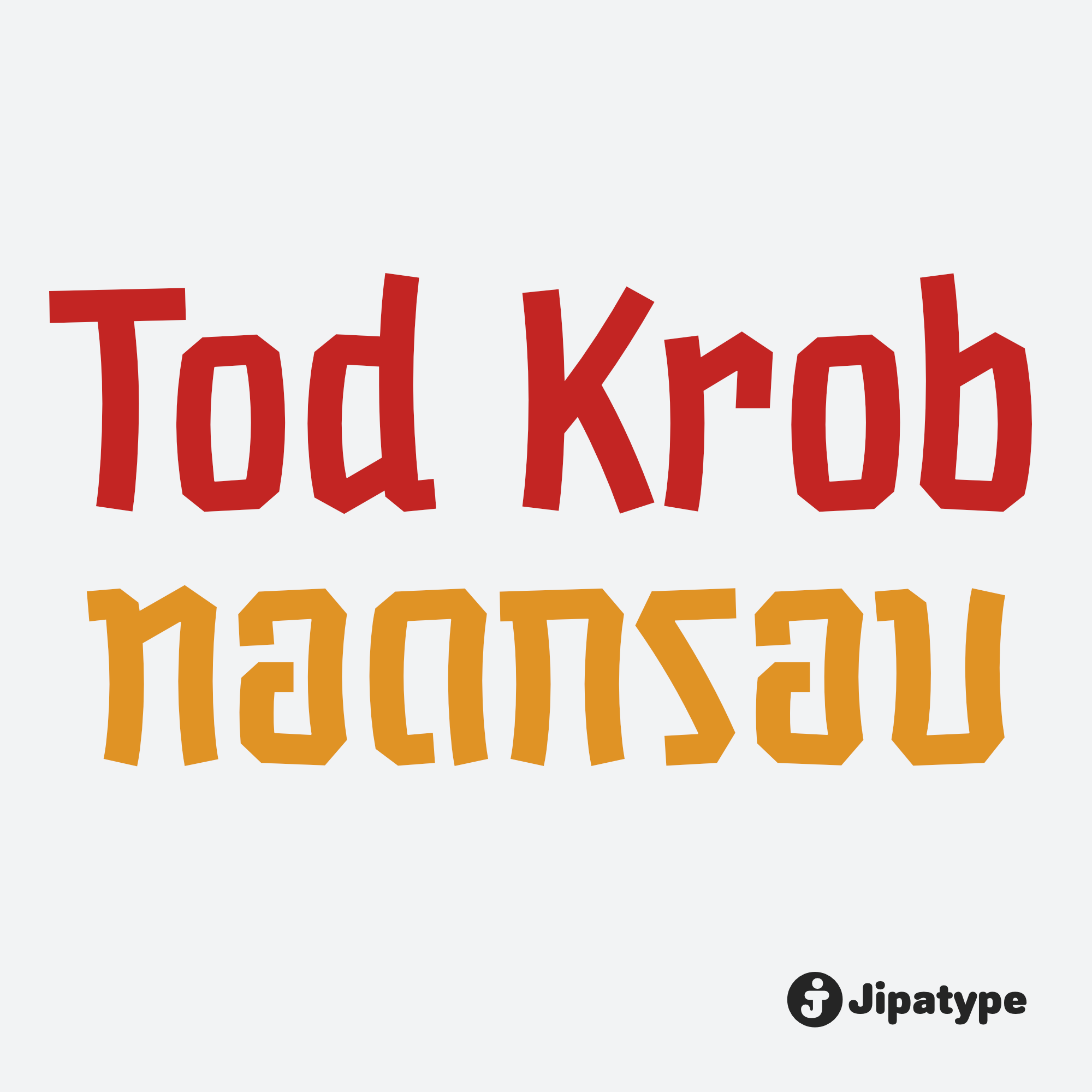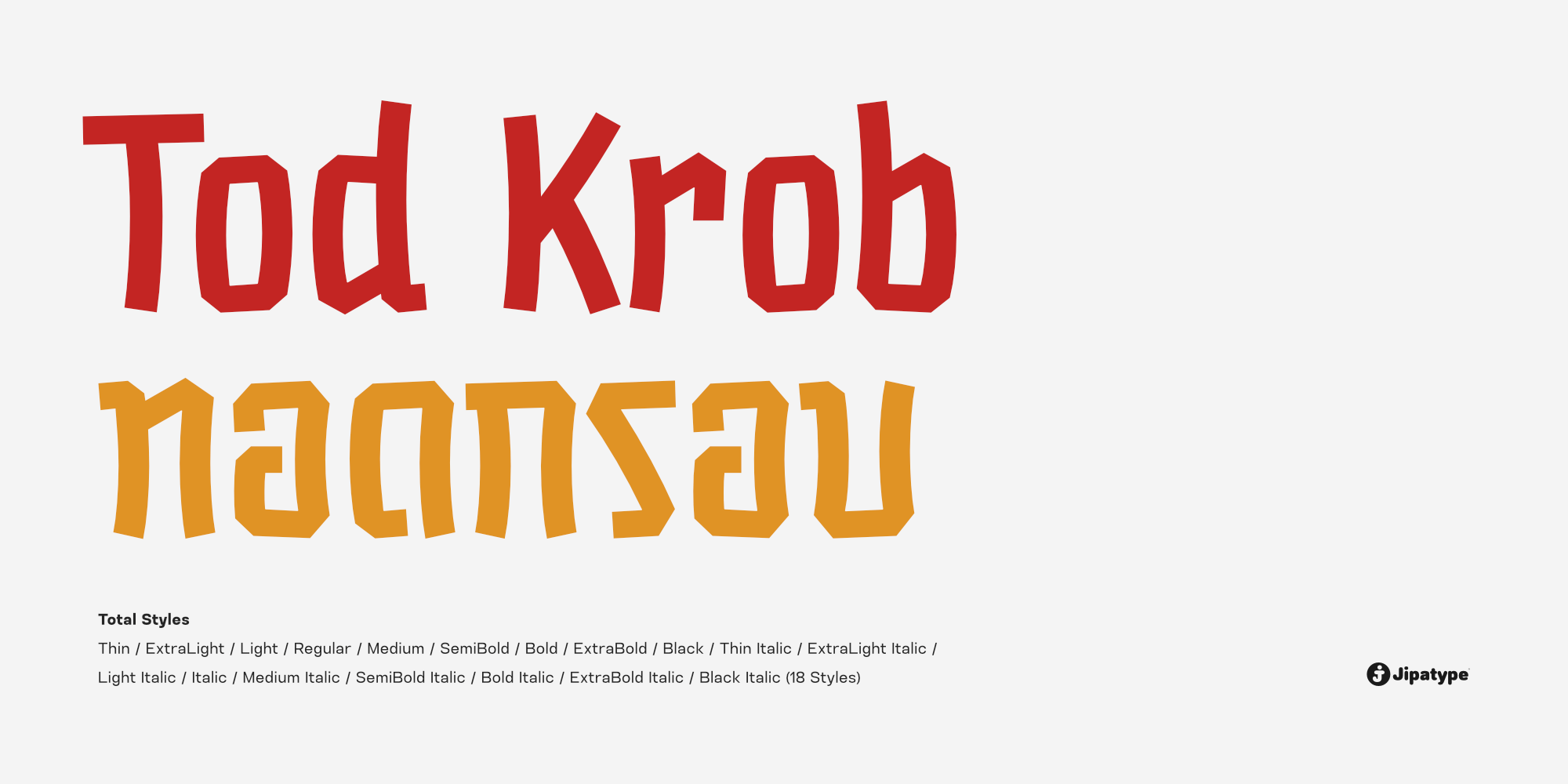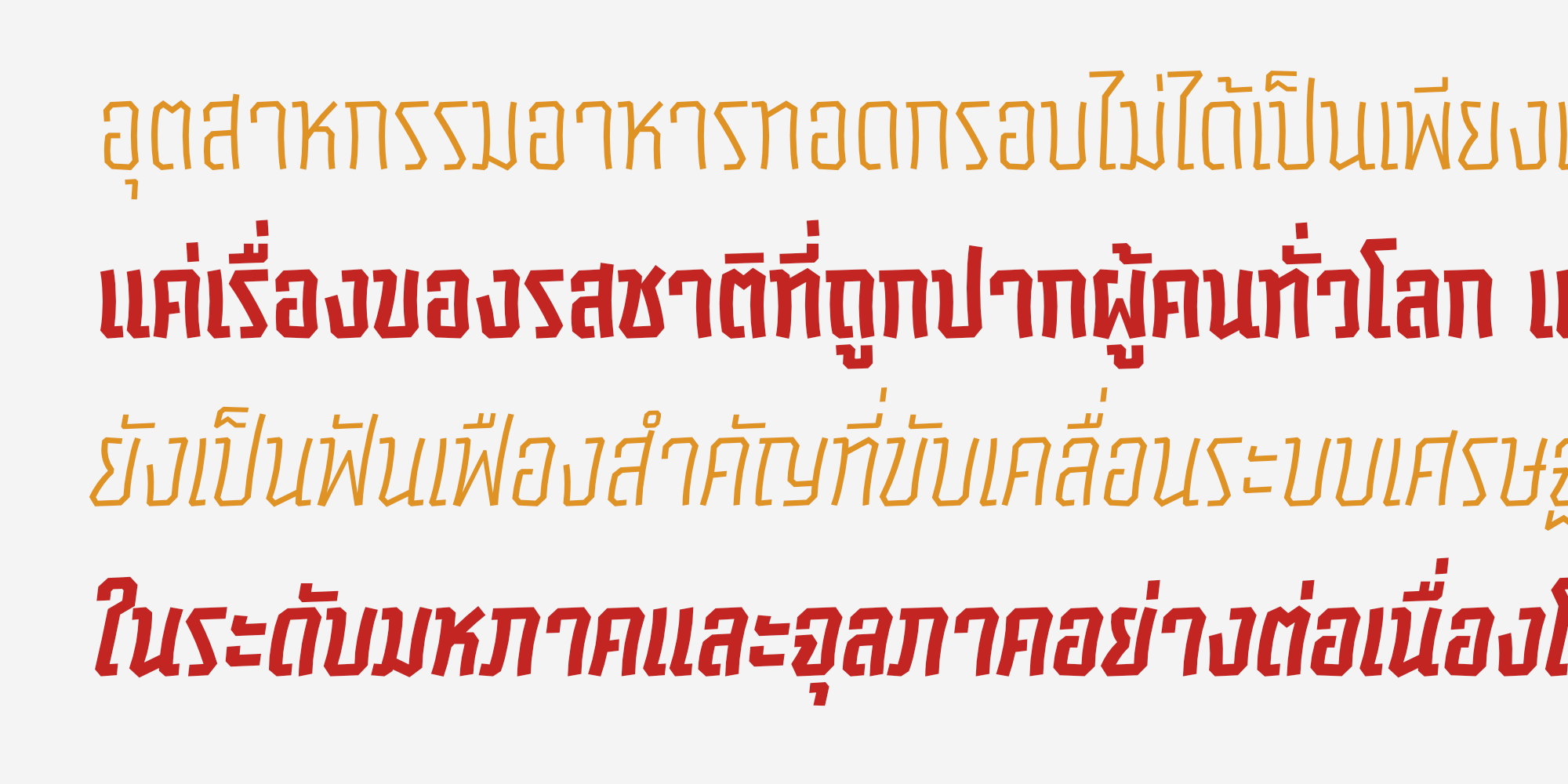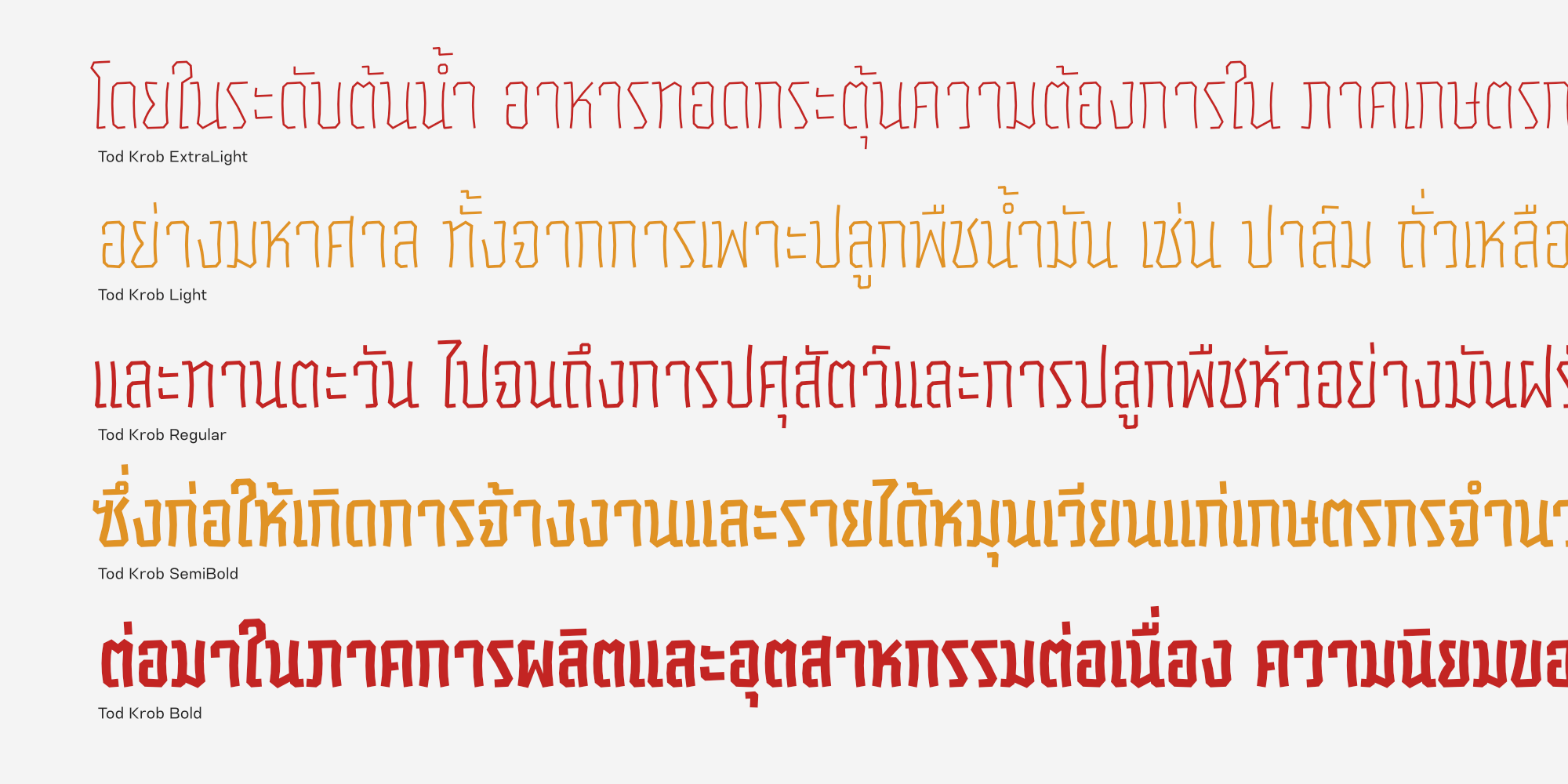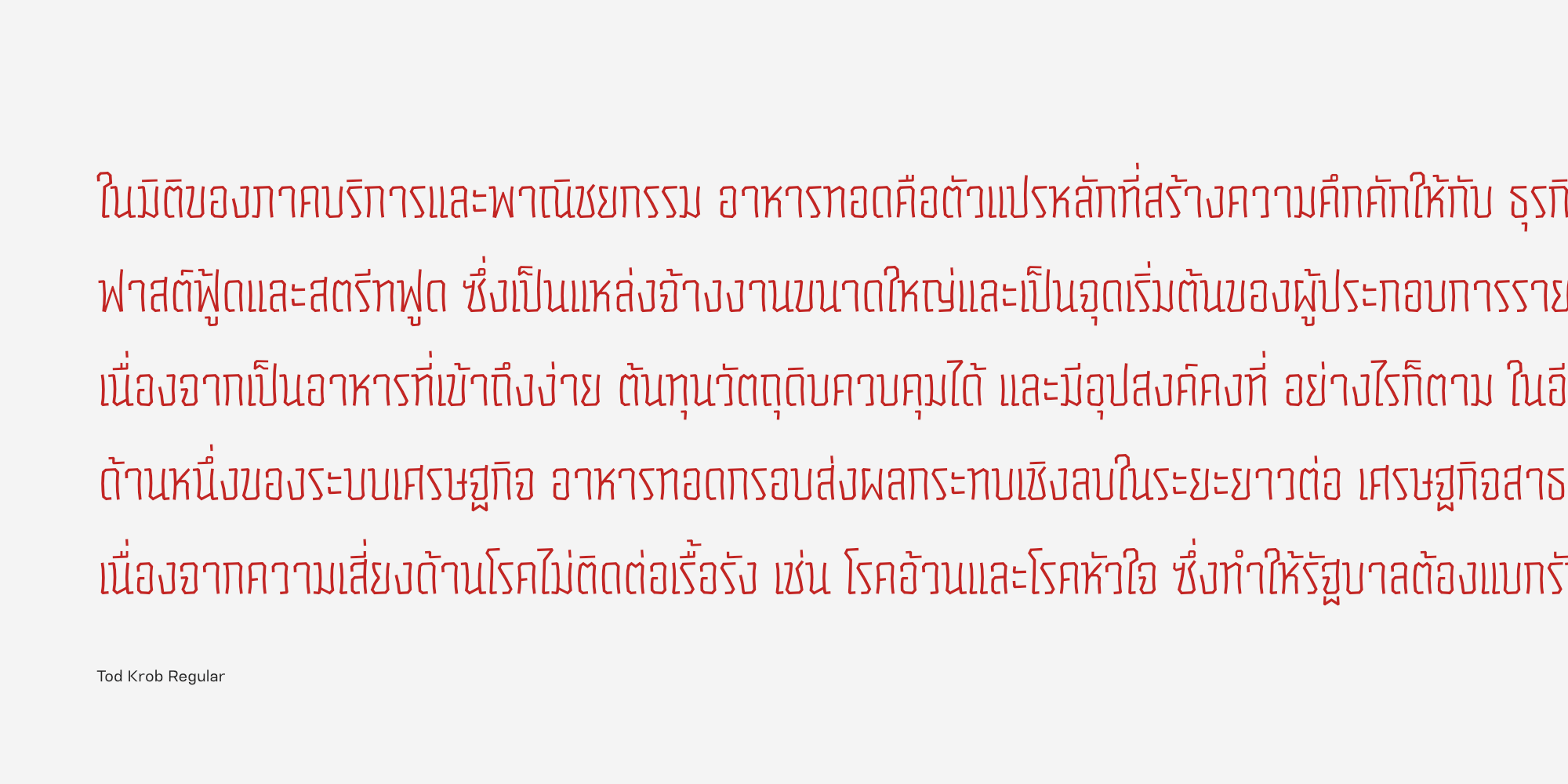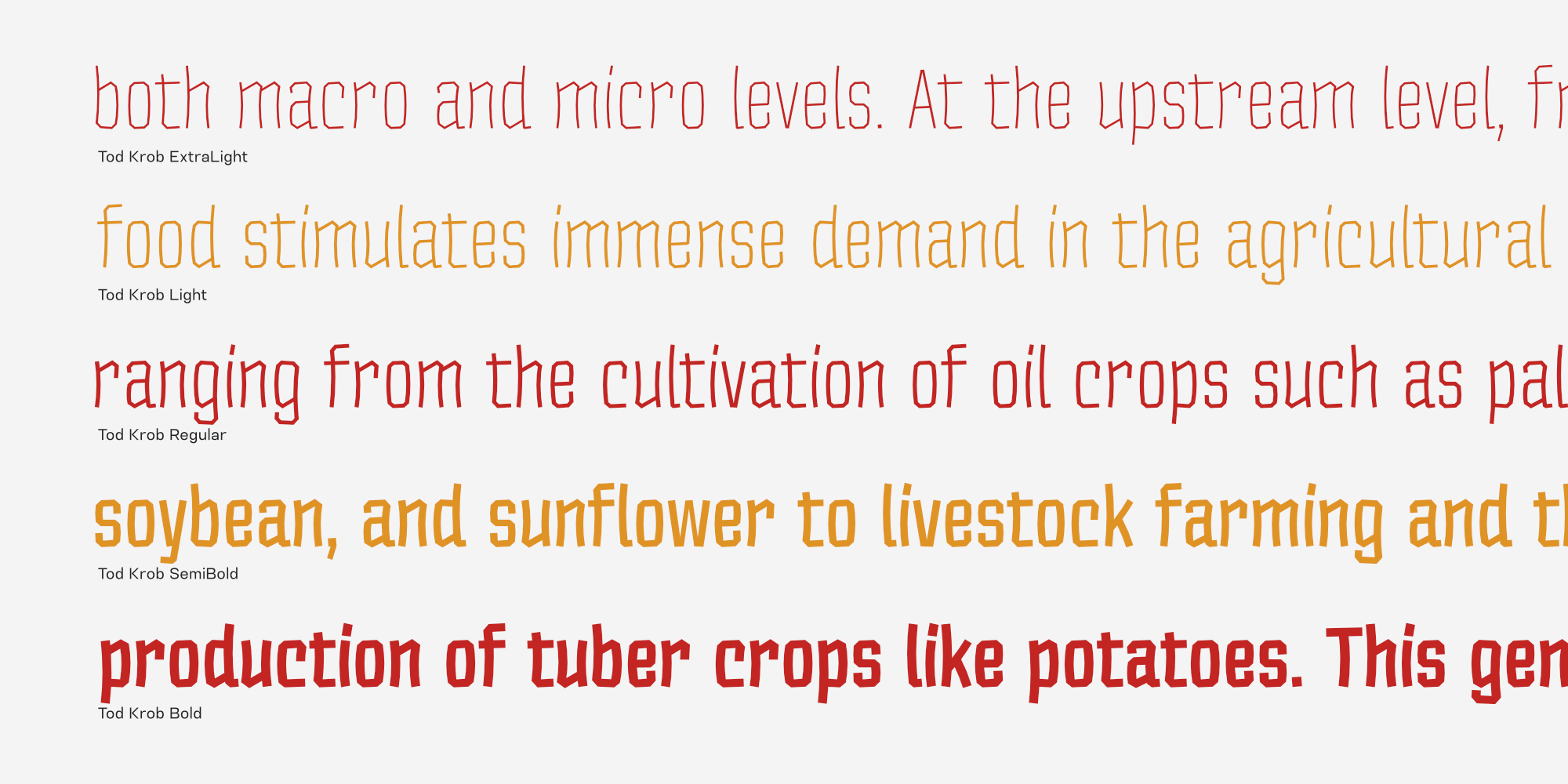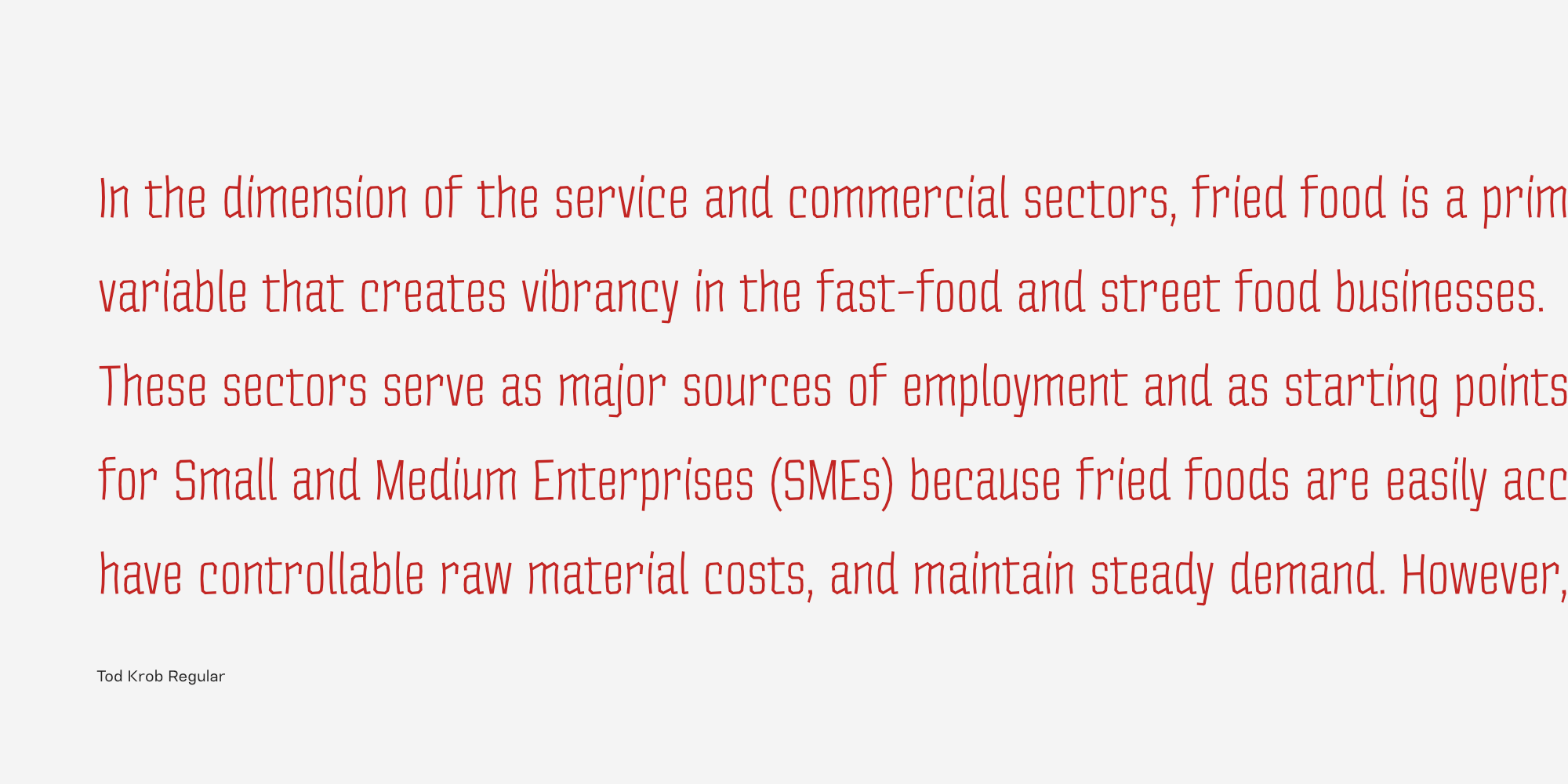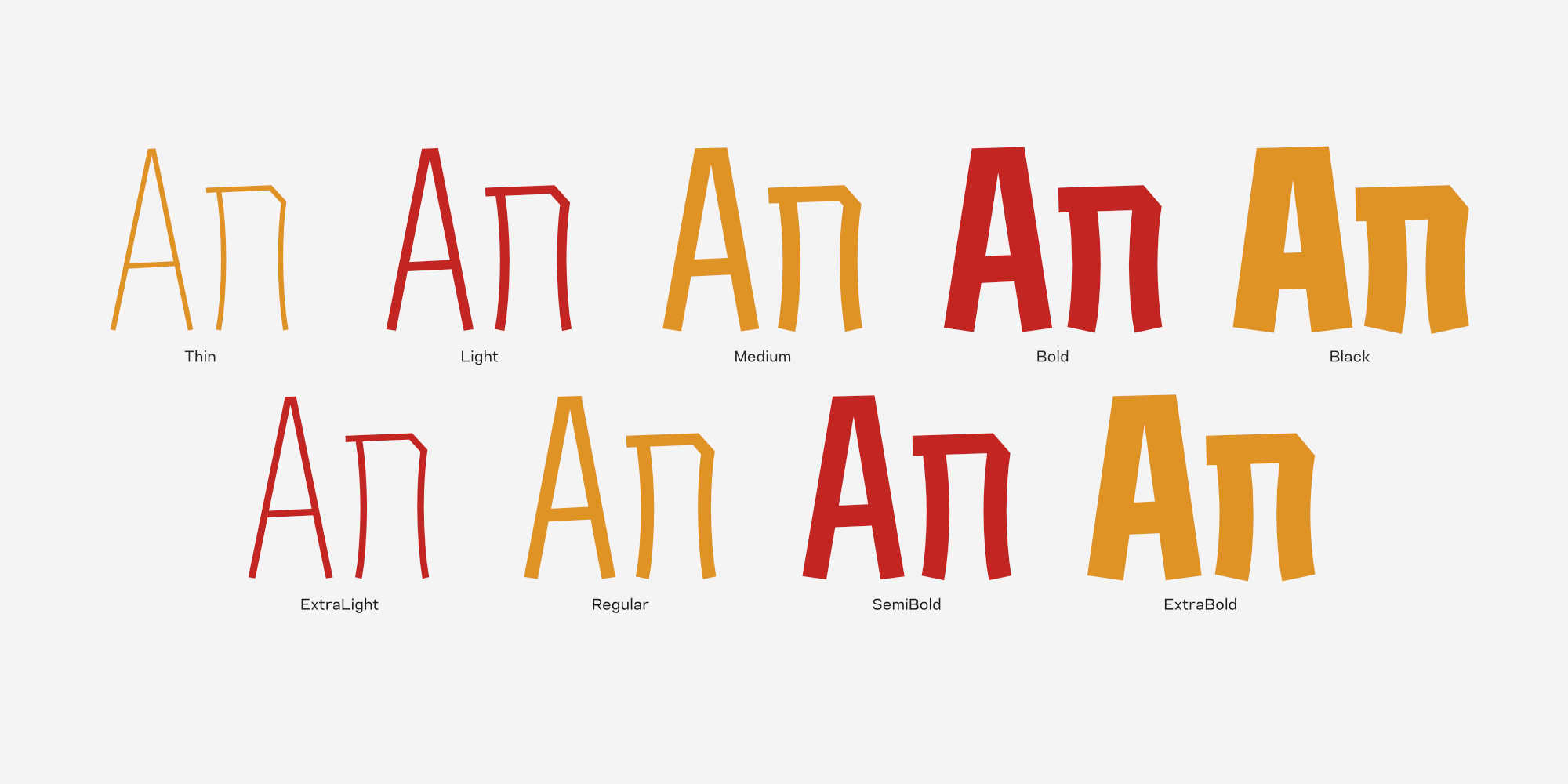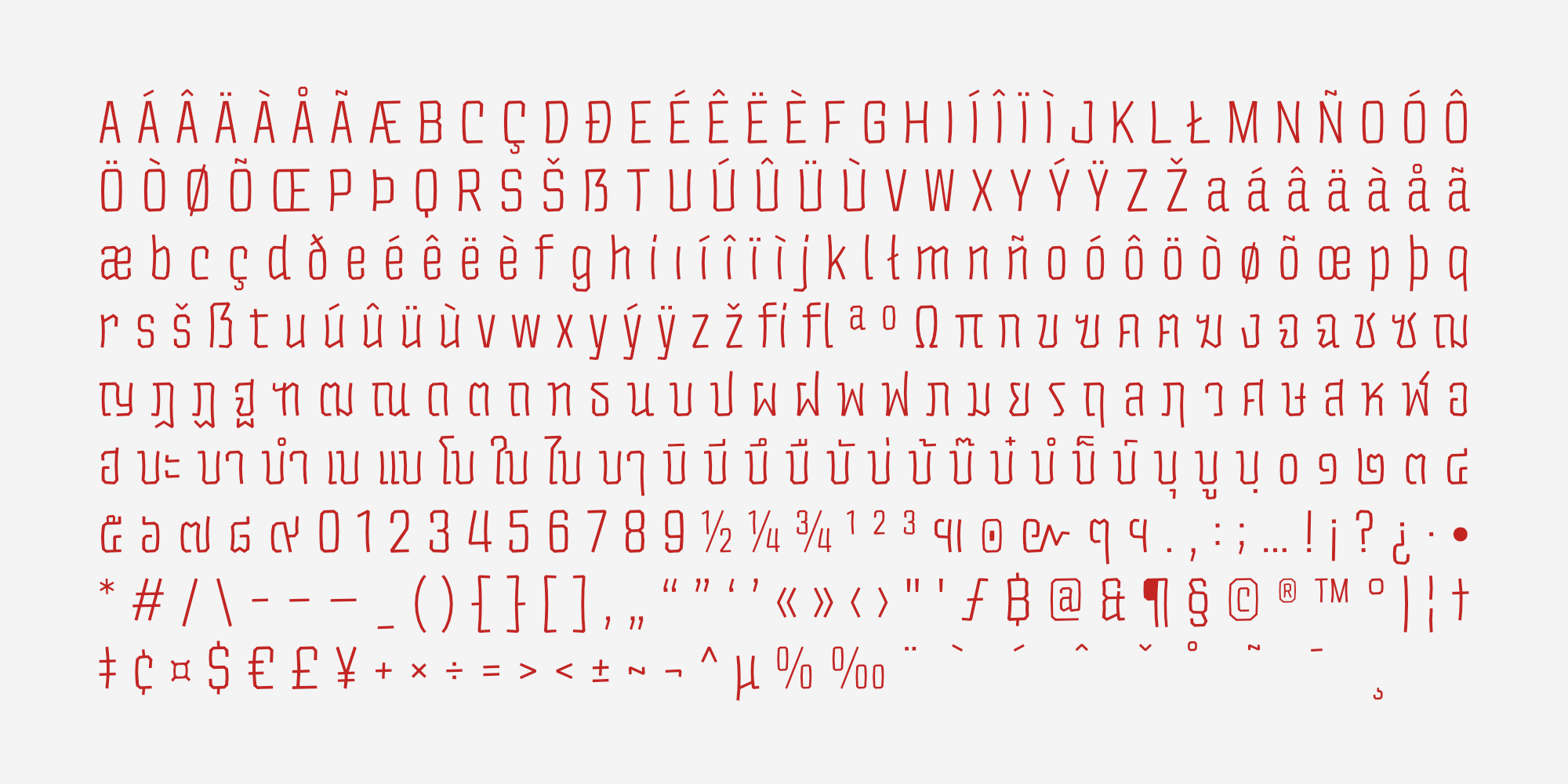
Tod Krob คือแบบอักษรชุด Condensed ที่เปี่ยมไปด้วยความสนุกสนาน โดยได้รับแรงบันดาลใจหลักมาจากรูปทรงอันเป็นเอกลักษณ์ของ “เฟรนช์ฟรายส์” ของทอดแสนอร่อย เส้นสายของตัวอักษรจึงถูกออกแบบให้มีความโค้งมนและหักมุมอย่างเป็นธรรมชาติให้มีความไม่สมมาตร เพื่อสร้างความรู้สึกที่เป็นมิตร เข้าถึงง่าย และดูมีพลังเคลื่อนไหวอยู่เสมอ
ตัวอักษรมีสัดส่วนที่ผอมสูงช่วยประหยัดพื้นที่ในการจัดวางเลย์เอาต์ พร้อมด้วยการออกแบบตัวอักษรไทยสไตล์ร่วมสมัยแบบไม่มีหัว ที่ดูสอดรับกับตัวละตินได้อย่างไร้รอยต่อ
Tod Krob มีให้เลือกถึง 18 สไตล์ ครอบคลุม 9 น้ำหนักตั้งแต่น้ำหนักบางเฉียบไปจนถึงหนามากพร้อมตัวเอียง ทำให้ Tod Krob มีความยืดหยุ่นสูงในการใช้งาน เหมาะอย่างยิ่งสำหรับงานสร้างอัตลักษณ์แบรนด์อาหารและเครื่องดื่ม ร้านอาหารฟาสต์ฟู้ด หรืองานออกแบบบรรจุภัณฑ์ขนมขบเคี้ยวที่ต้องการความสดใสและน่าดึงดูด
นอกจากนี้ยังทำงานได้ดีในงานพาดหัว โปสเตอร์โฆษณา หรือสื่อดิจิทัลที่ต้องการบุคลิกขี้เล่น และมีความเป็นกันเอง ถือเป็นเครื่องมือทางการออกแบบที่จะช่วยเพิ่มความ “กรอบ” และความโดดเด่นให้กับการสื่อสารได้อย่างมีชีวิตชีวา
ออกแบบโดย : อานุภาพ ใจชำนาญ (Anupap Jaichumnan)